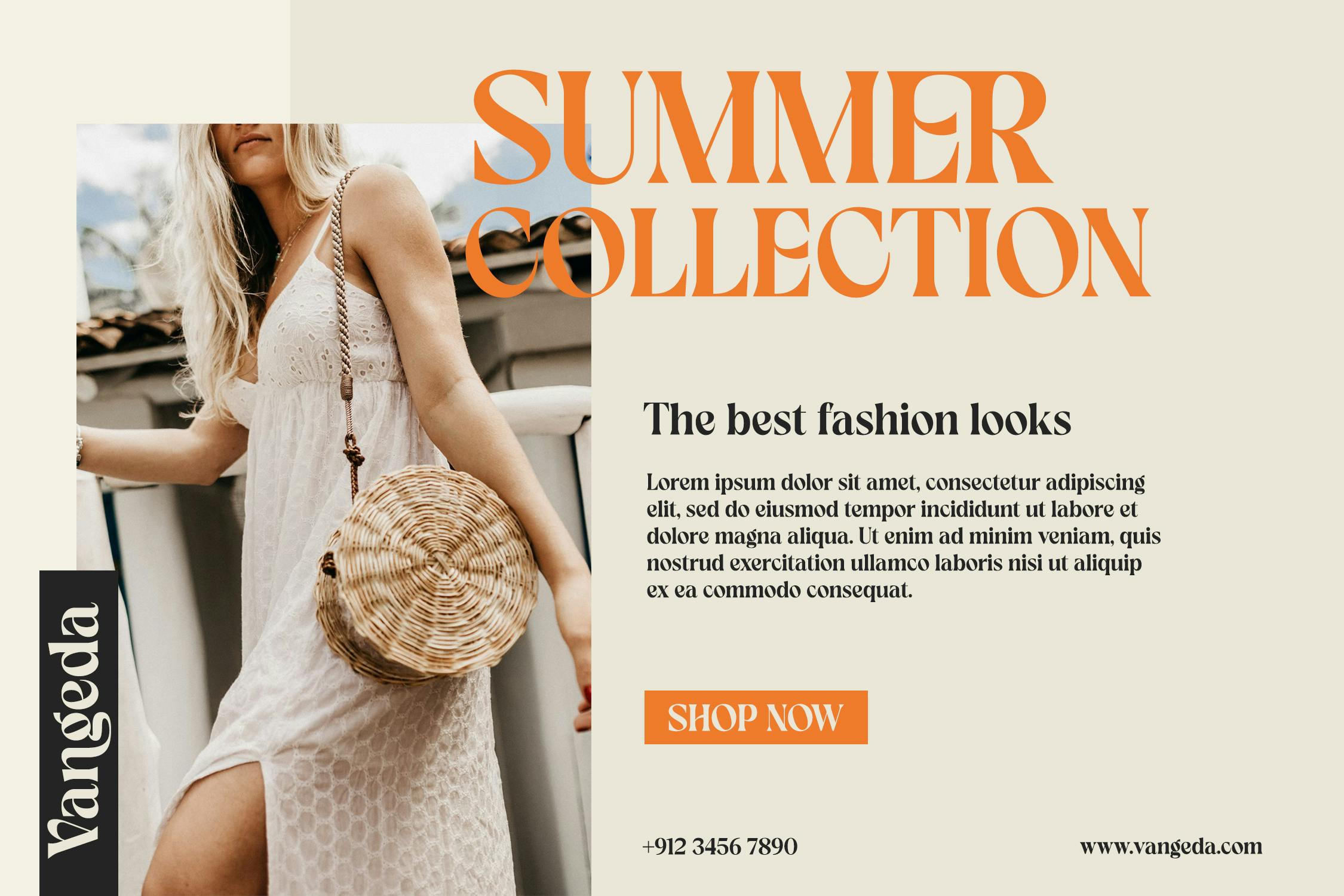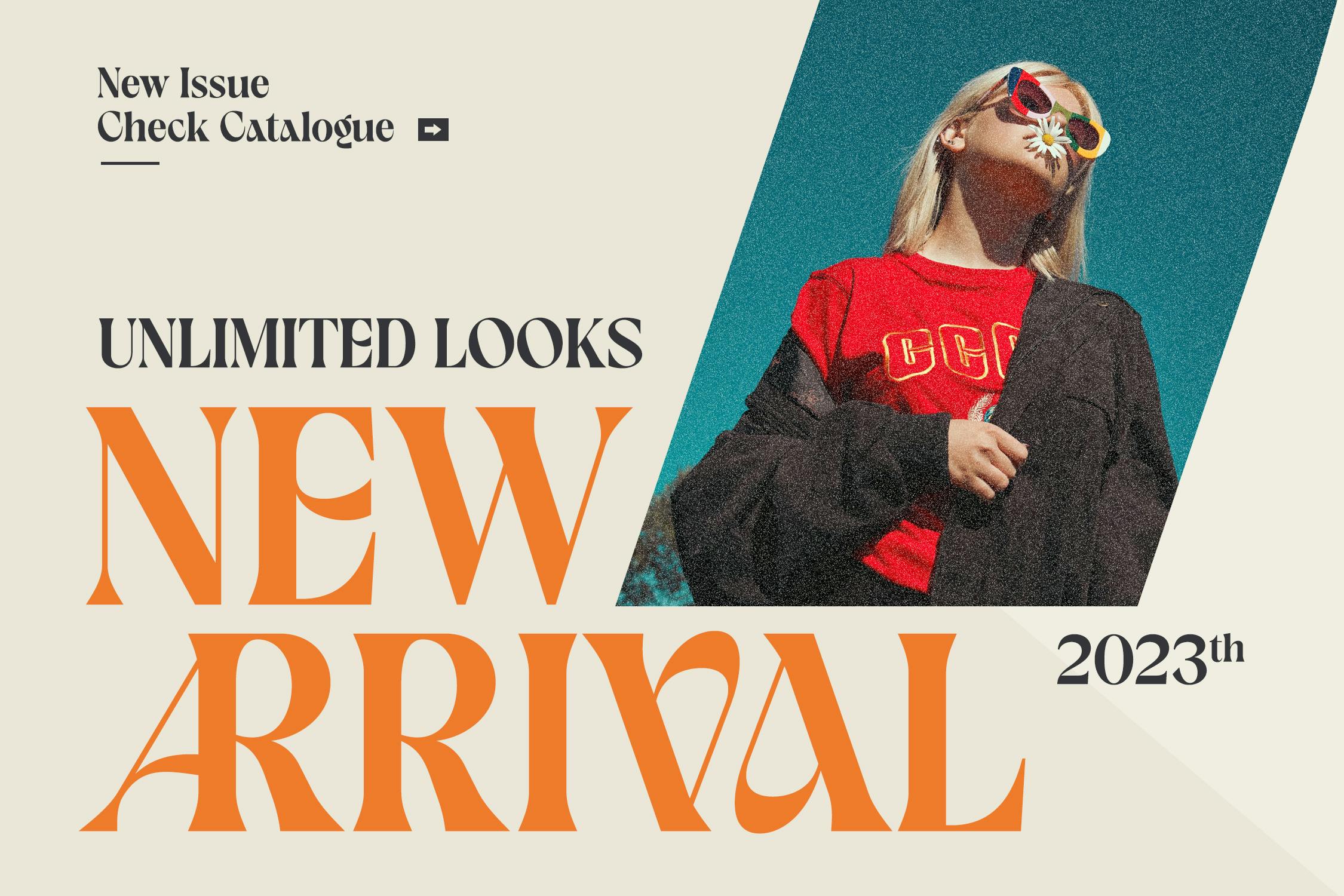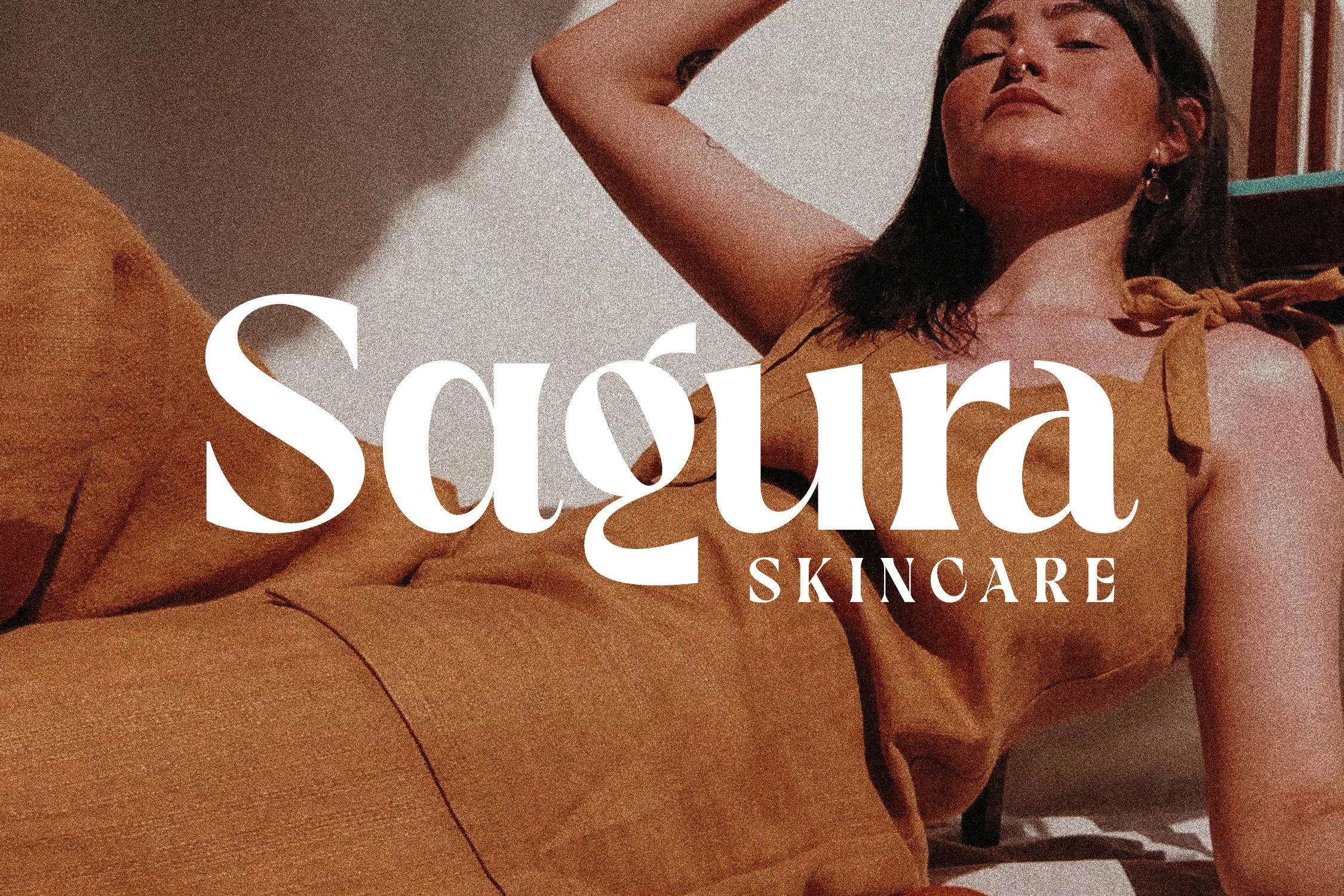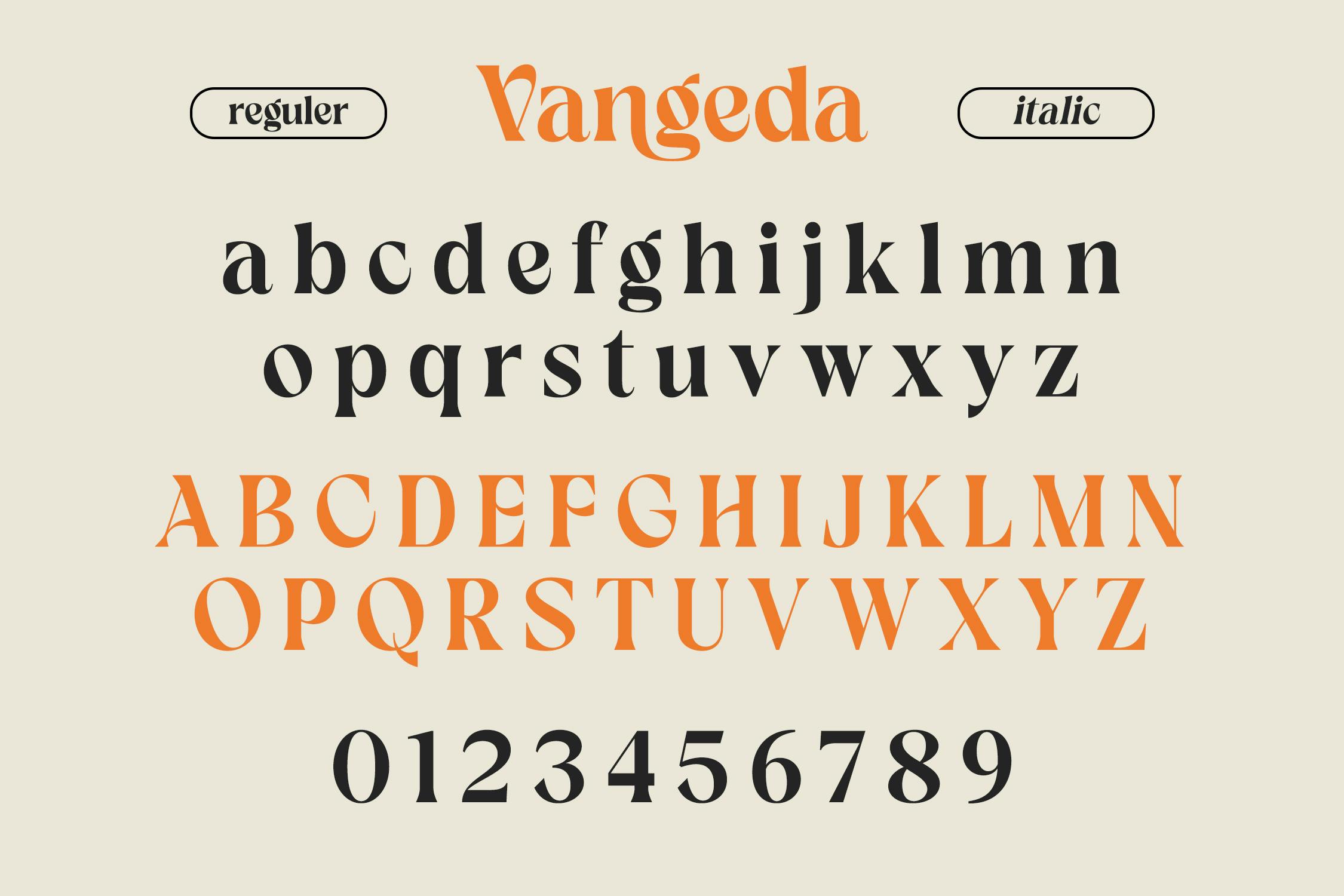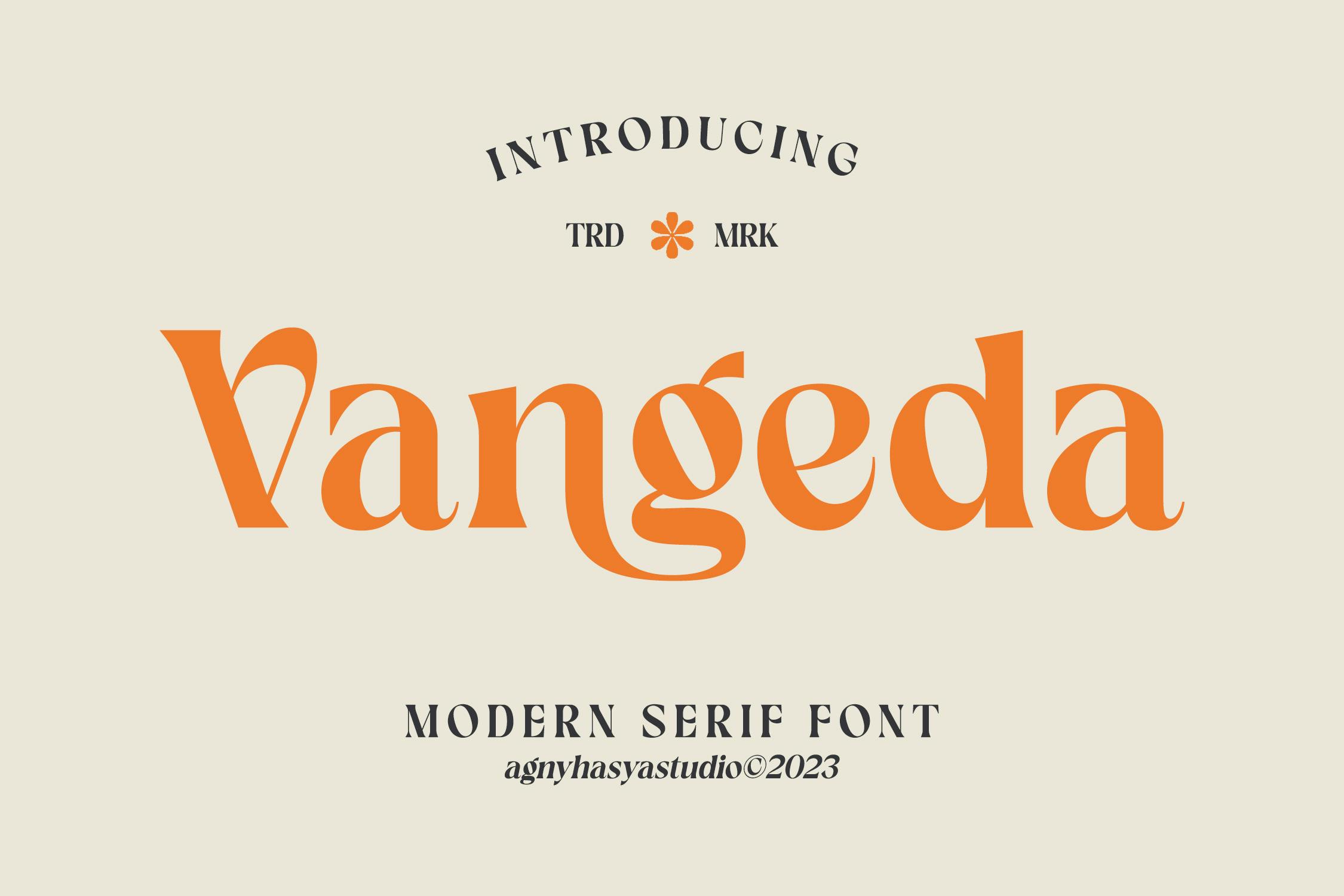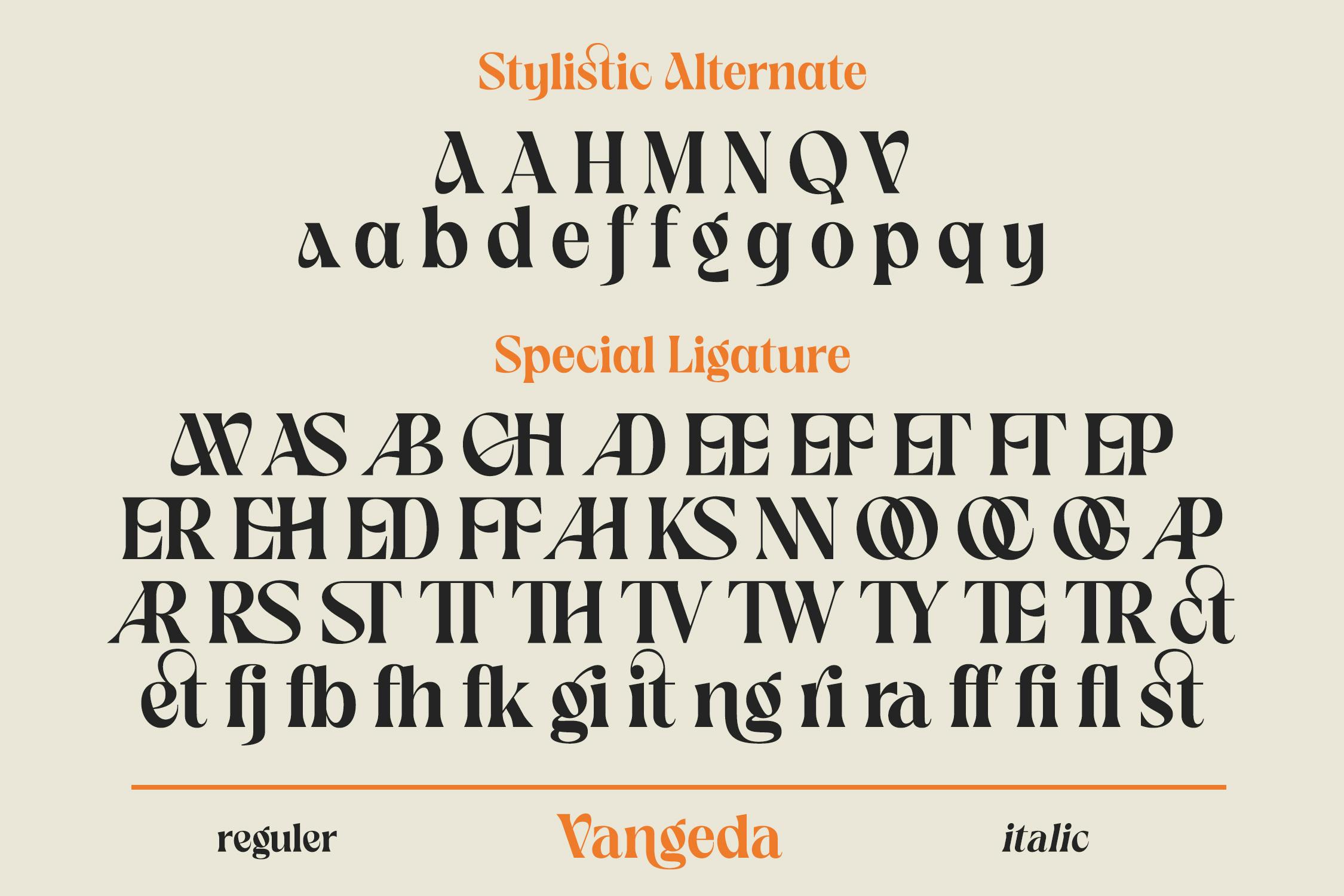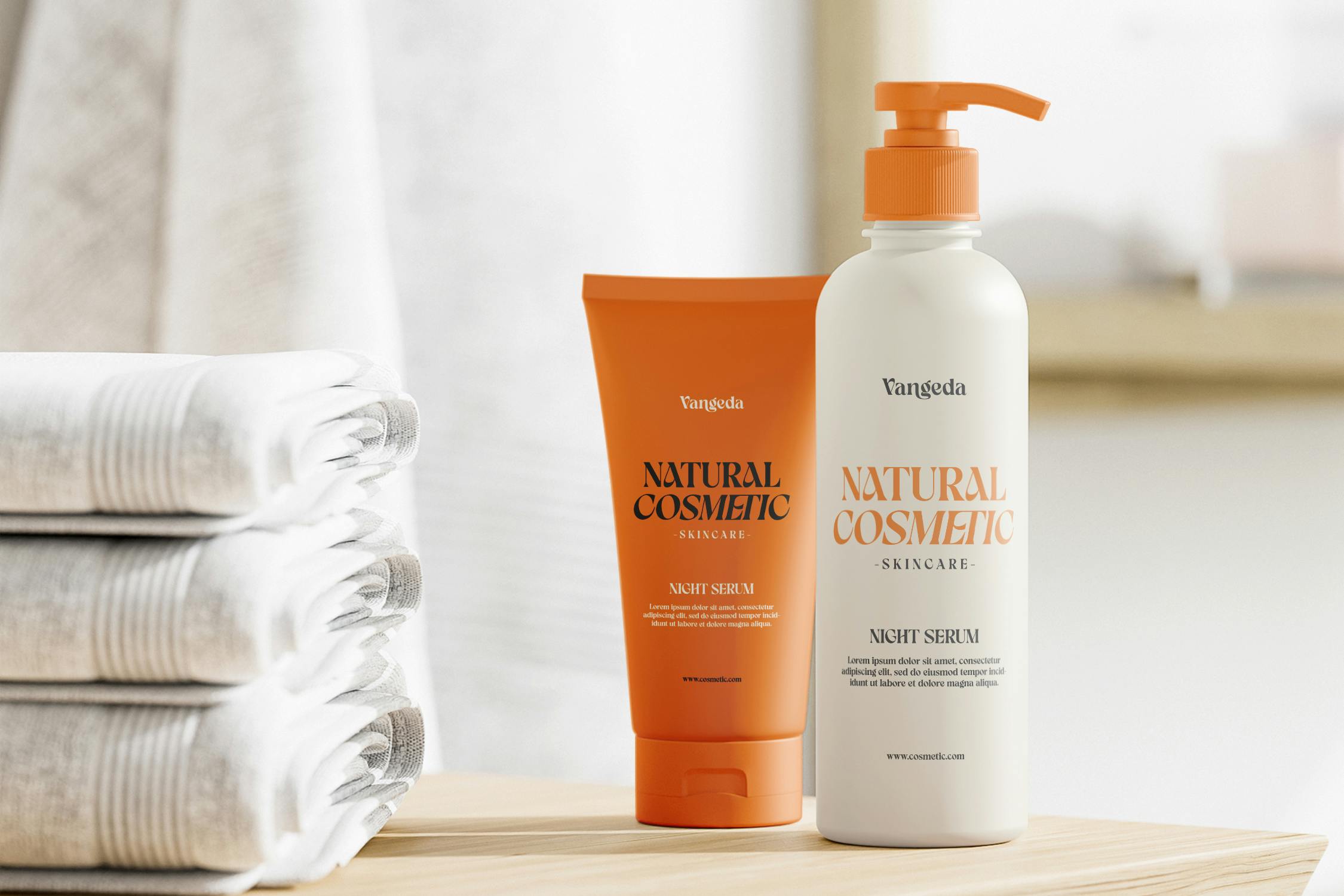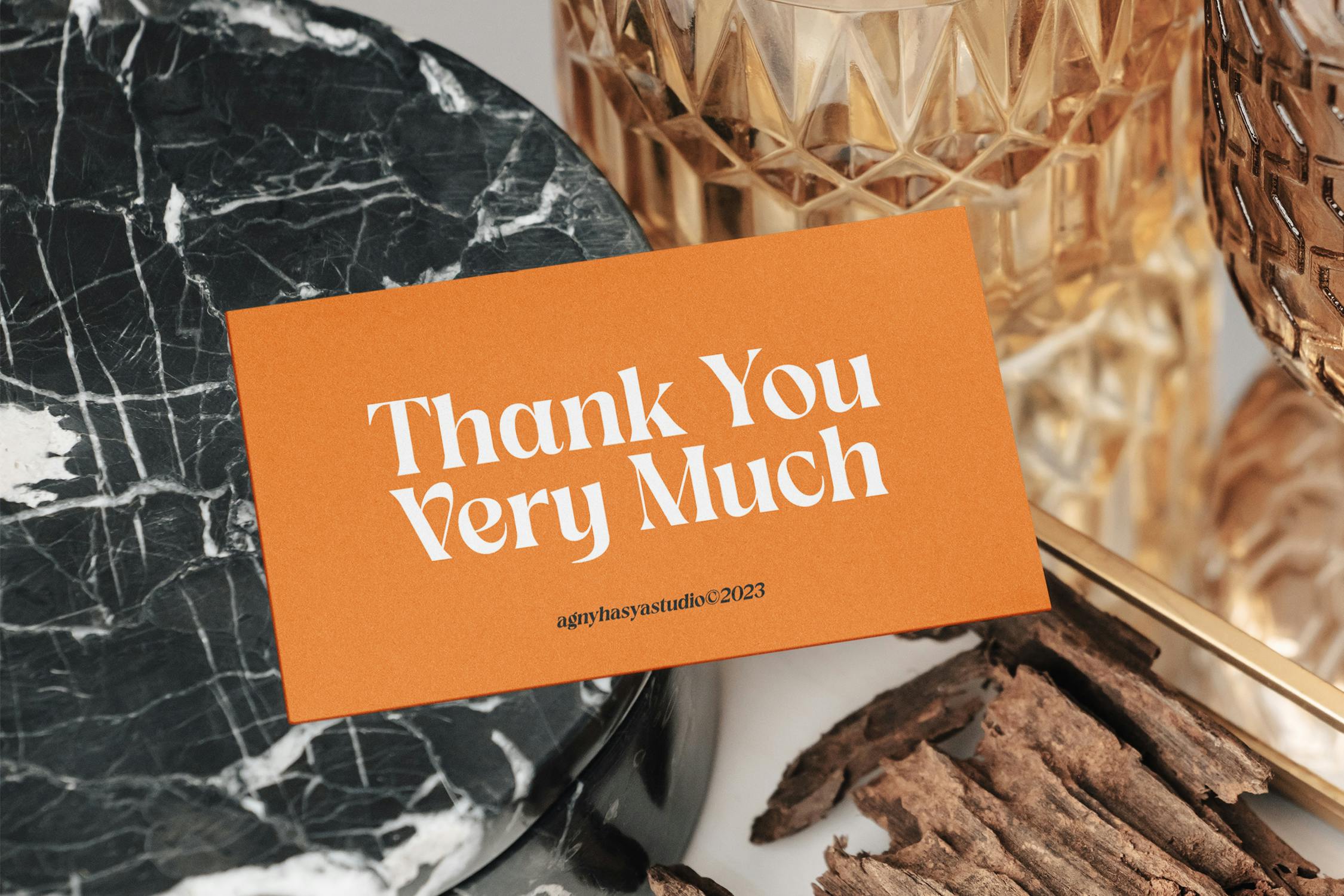
معرفی فونت ونگدا – فونت سریف مدرن
ونگدا یک فونت سریف مدرن و باوقار است که با دو سبک (عادی و کج) و تنوع گلیفی همچون جایگزینها و لیگاتورها طراحی شده است. این فونت را ترکیب کنید و طراحی تایپوگرافی ایدهآل خود را بسازید!
این فونت برای پروژههای طراحی شما مانند لوگوها، برندینگ، تبلیغات، طراحی محصولات، لوازمالتحریر، طراحی مجلات، طراحی عنوان کتاب/کاور، عکاسی، نقلقولهای هنری، طراحیهای عروسی، طراحیهای مد، رویدادهای خاص، برچسبها، بستهبندی محصولات و موارد دیگر بسیار مناسب است.